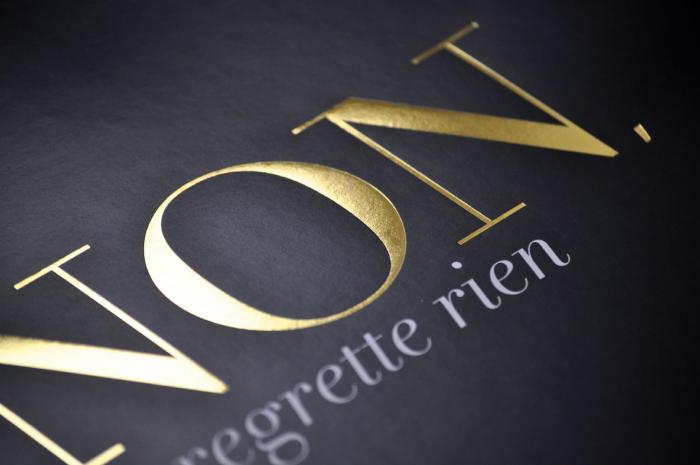
Kennt jemand diese Schrift? Bitte um Hilfe.
könntet Ihr mir bitte sagen in welcher Schrift bzw. Variation das Wörtchen "NON" verfasst ist und ob diese oder eine
Sieht mir nach einer Didot aus – allerdings das eine güldene Komma am Ende, das passt nicht so recht ins Bild. Vllt. ist das dazugedichtet. (?)
(Nee, die Walbaum ist es nicht.)
… unter bertels link gibts übrigens beide kommavarianten zu sehen.